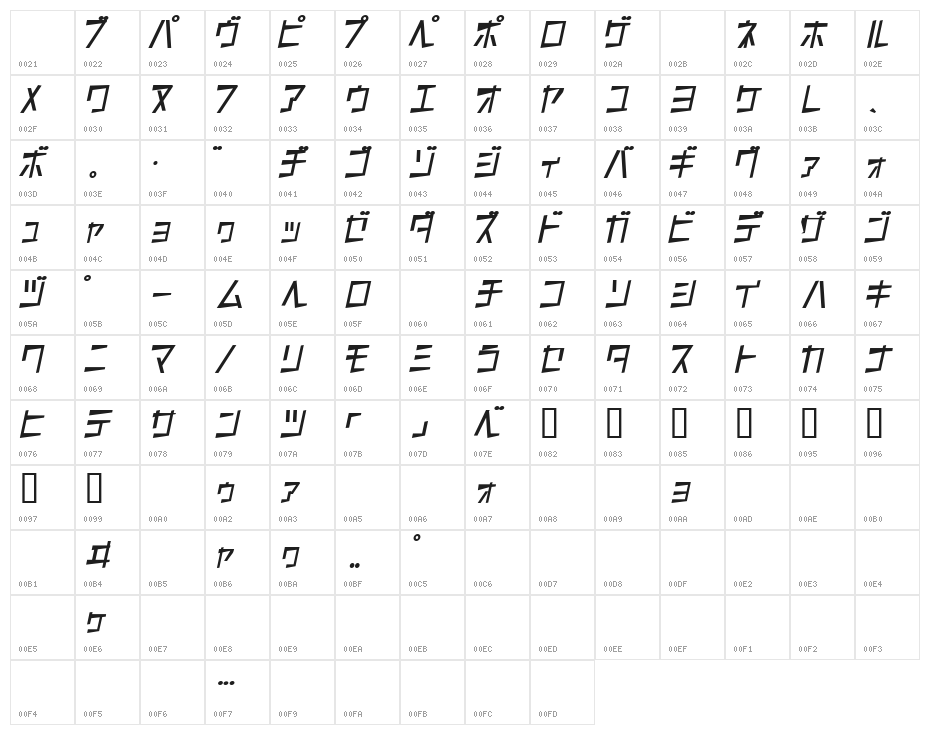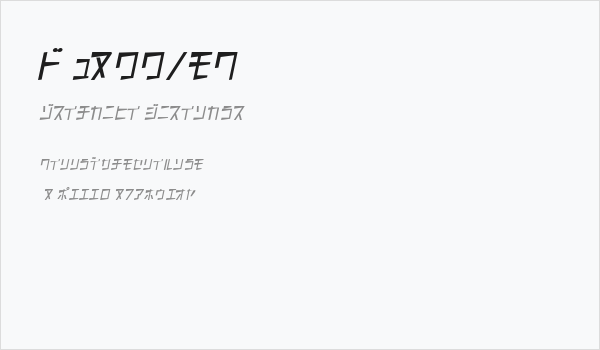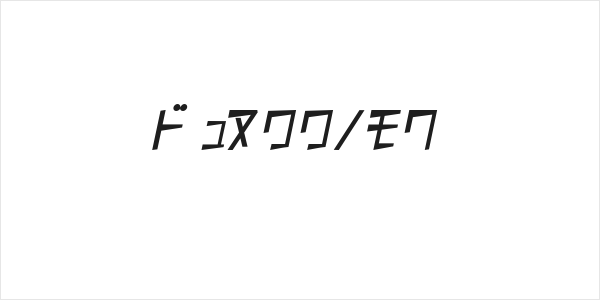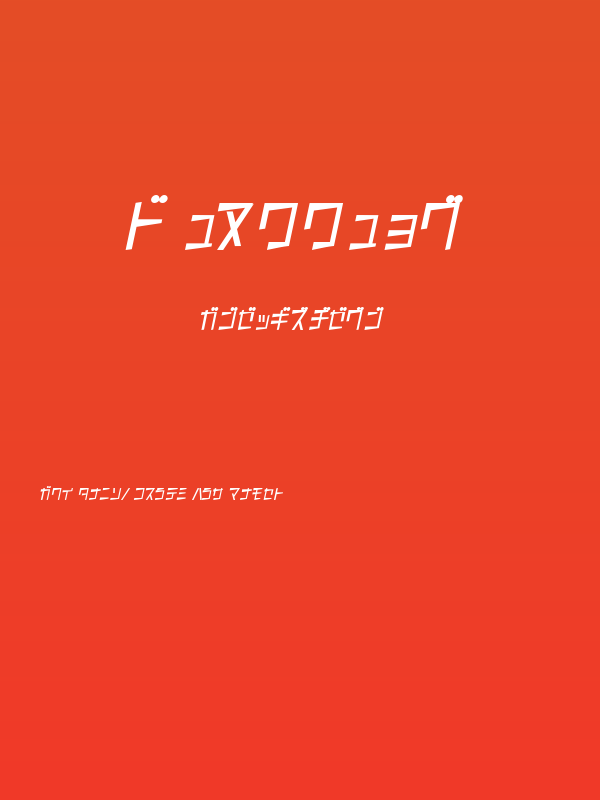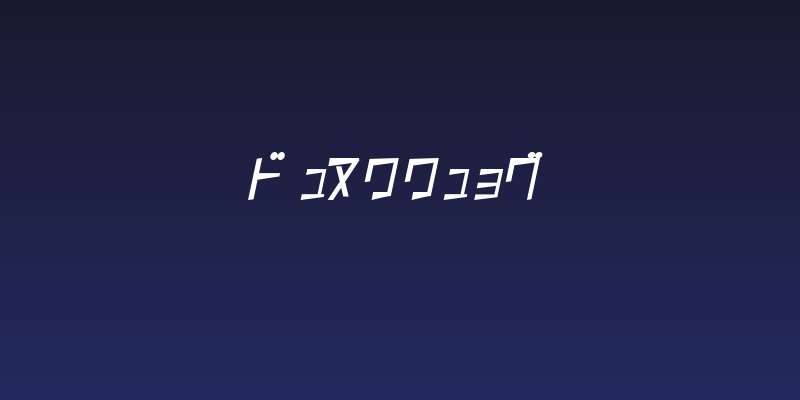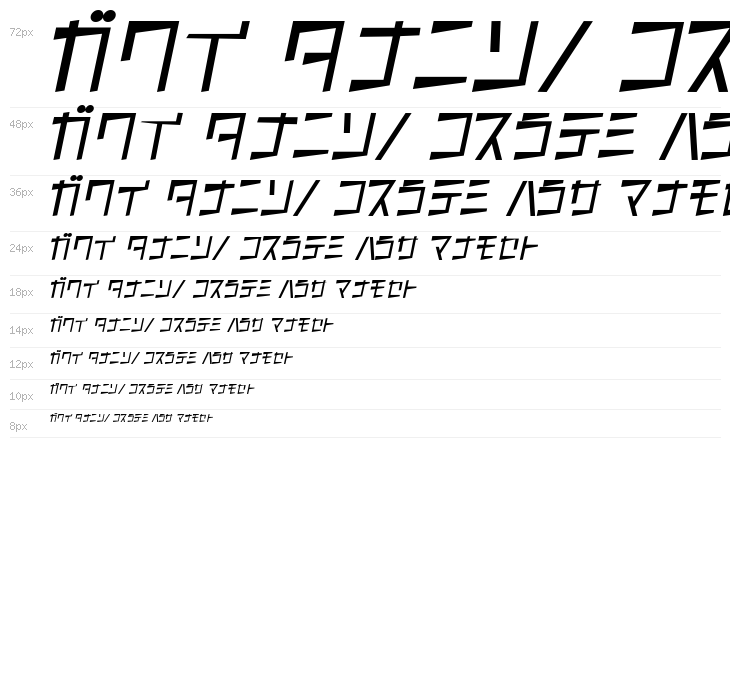
S K100kmh Font
| Progetti proposti | Ideal for projects related to technology, gaming, or any futuristic themes. Suitable for branding, posters, and digital media that require a modern and edgy look. |